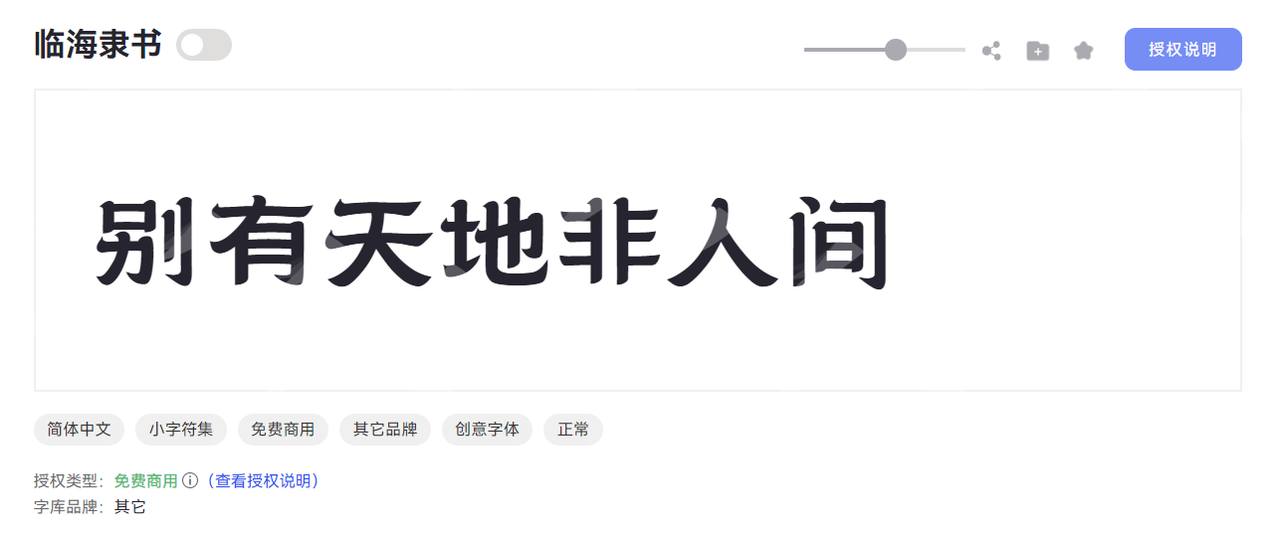
不用书法功底!这个在线工具一键实现隶书转换
在设计行业,书法字体一直是很受欢迎的字体选择。不管是品牌包装、文创国潮设计,或者是海报设计,日常生活的很多场景中都离不开书法类字体,隶书更是深受大家的青睐。由于其“蚕头燕尾”的笔画特性,经常能传递出一种古朴典雅、端庄大气的视觉氛围。令人头疼的是,系统自带的隶书字体选项较少,做设计时不能充分满足大家的需求;网上搜集来的字体又需要复杂的安装下载过程,可能还要花费大量时间查找版权问题。今天就给大家介绍一个在线隶书转换工具——字由,无需下载安装字体,简单几步就能完成隶书转换,让你的作品瞬间拥有古典优雅的气质韵味。
三、字由内的隶书字体资源推荐
1.临海隶书
临海隶书是一款融合传统隶书韵味与现代创意美学的简体中文创意字体。字体以扁宽字型为核心特征,整体形态开阔舒展,每个字符都显得端庄大气,适合作为视觉焦点元素使用。 临海隶书的笔画设计以利落直角线条为主,转折处融入细腻装饰元素,既保留传统隶书的骨感,又增添现代设计的灵动细节。
2.汉仪中隶书简
汉仪中隶书简是一款现代化的隶书字体,整体视觉上具有流动性,比传统隶书更加活跃。字形略扁近乎于方,笔画干净利落、结构紧凑,又兼具生动优美,特别适合标题与标注性文本,以及小段文本的排版。
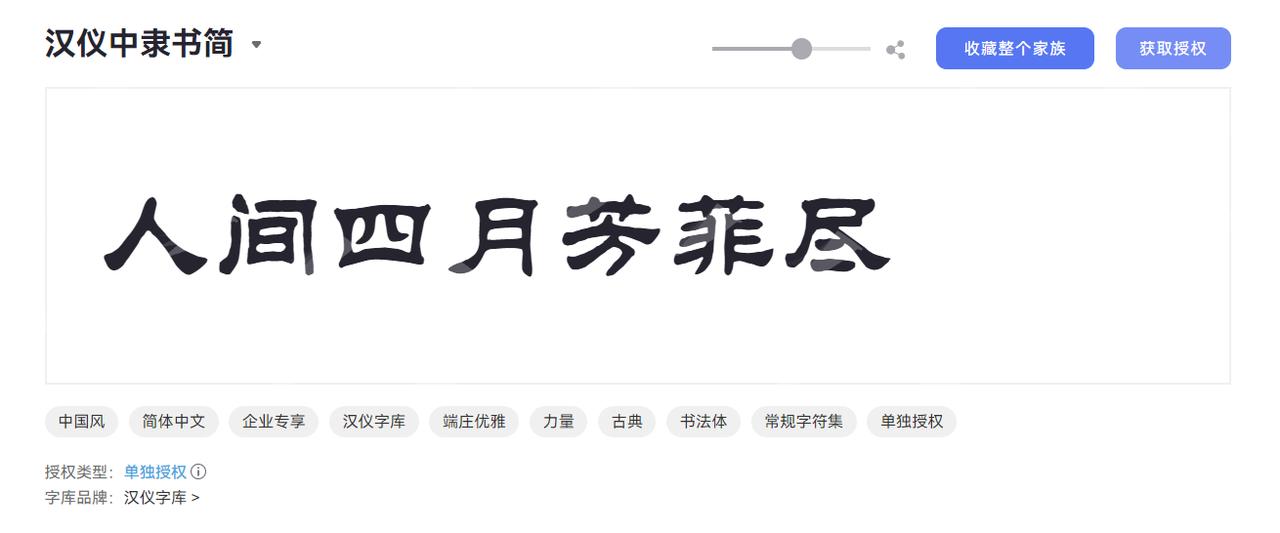
3.汉仪范笑歌隶书简
汉仪范笑歌隶书以不仅具有魏碑的笔画笔意,还有篆书的韵味风格,个字体风格刚柔相济,潇洒舒展。其中的范横画是范体隶书特有独创的笔画,范横画多在字的上部出现,如同舒展的双翅,使隶书中的蚕头燕尾更张扬,更有力度,整具有很强的装饰性。
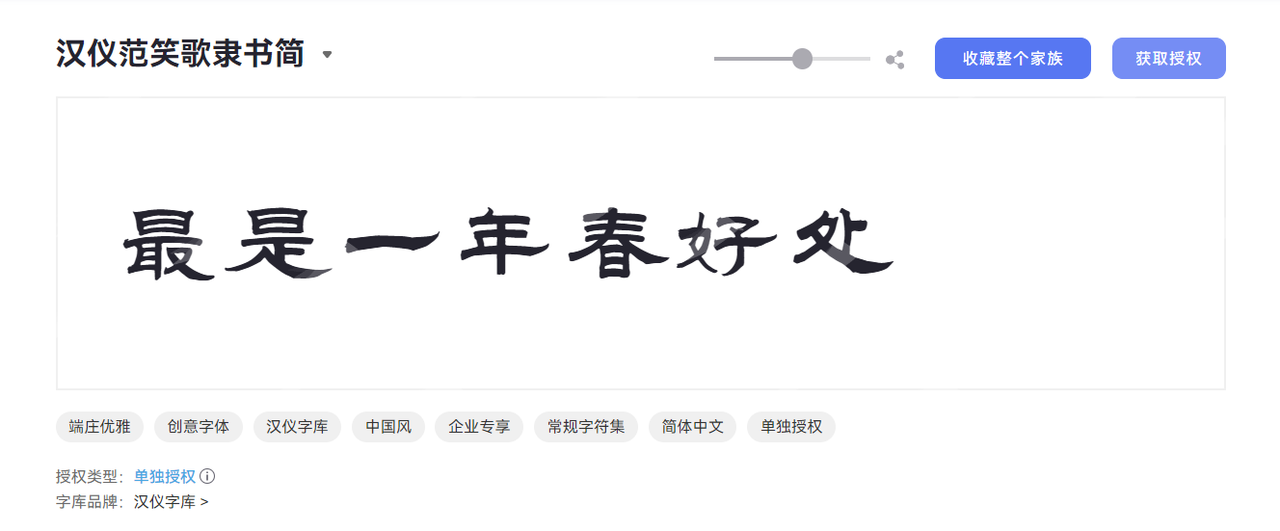
4.汉仪明瑾隶书
汉仪明瑾隶书是由中国硬笔书法协会会员郑明瑾先生创作的一款遒秀娴逸的隶书字体,以《曹全碑》为蓝本。它的笔画舒展飘逸,柔中带刚,赏心悦目。该字体最大的特点,在于字体内有相当多的字形采用了古代碑帖中存在过的异体字,可以为排版段落营造一种趣味性。这款字体适合用在文化展会、艺术创作等文化交流场合。
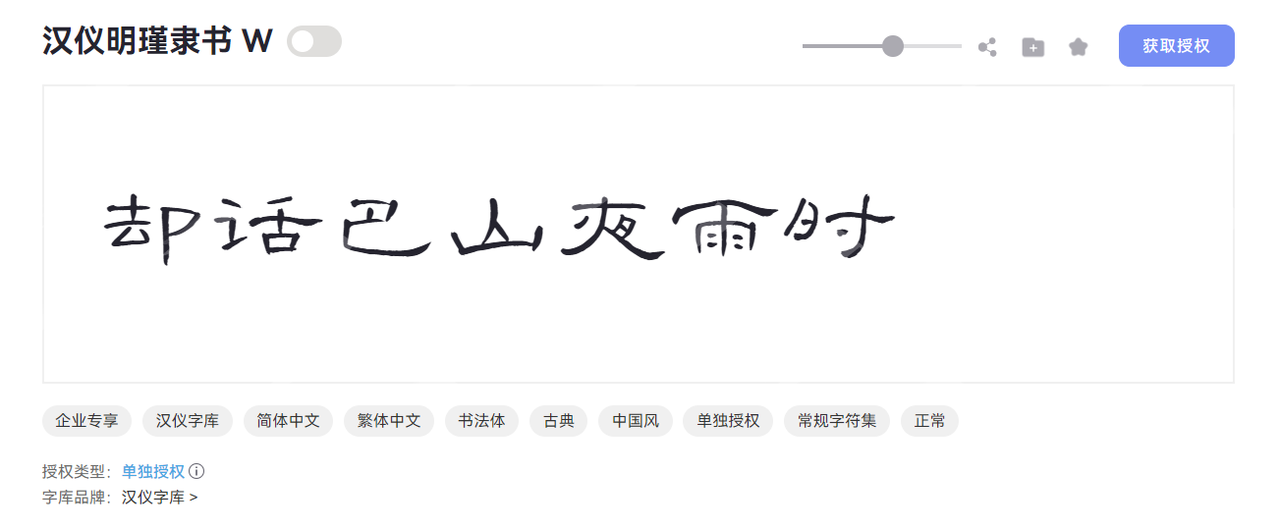
5.点字小隶书
点字小隶书是一款装东的隶书风格字体,在传统隶书基础上增添了独特的点状装饰元素。书写效果略微宽扁,横画长而直画短,呈长方形状。字体风格活泼,与简约正文搭配时层次分明,能有效提升视觉冲击力。